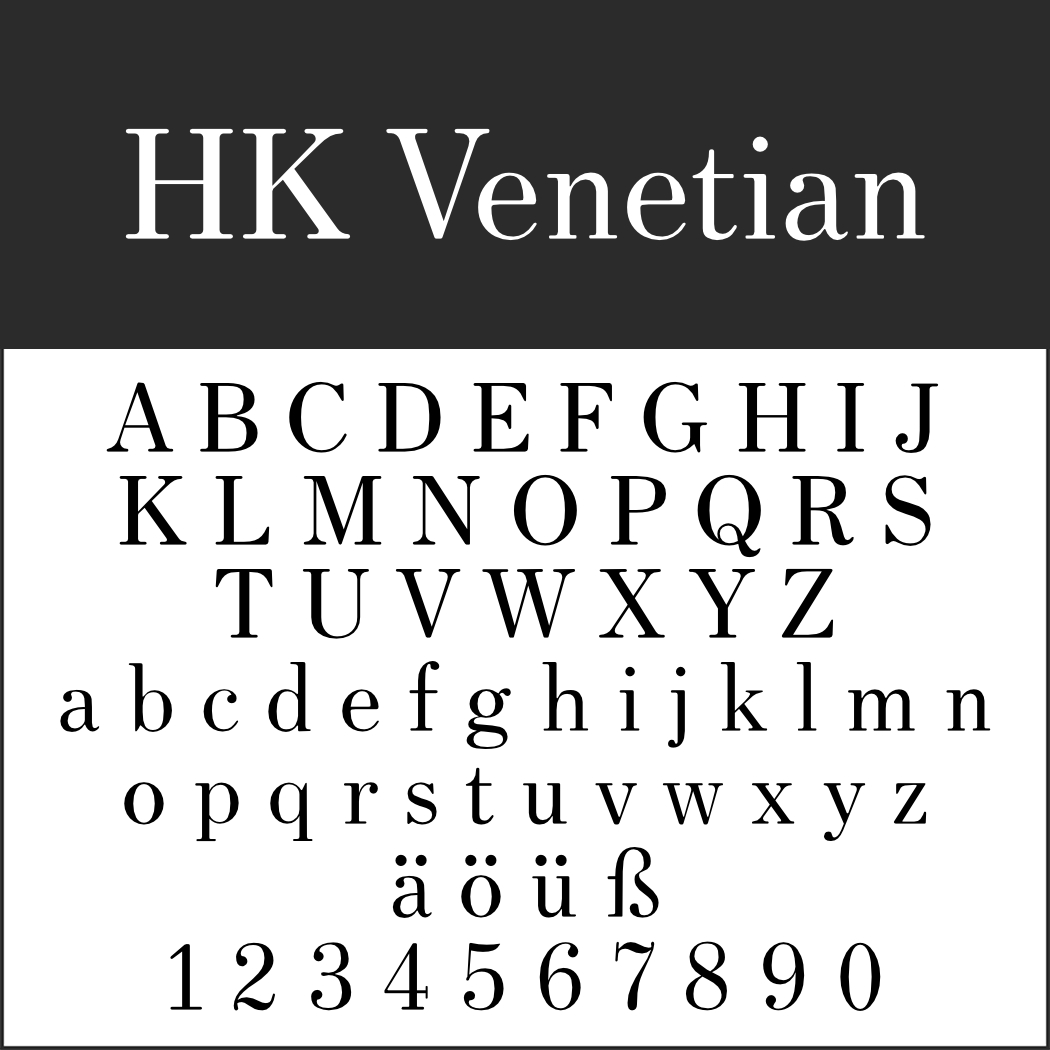
Schlichte Schriftarten lassen uns zunächst eher an Groteskschriften denken. Aber auch Serifenschriften können durchaus einfach wirken. In unserer Auswahl finden Sie beides.
Anek Telugu
Der indische Font aus Mumbai bietet acht Schriftstärken von Thin bis ExtraBold und ist deswegen sehr vielseitig einsetzbar.
Pianaforma
Pianaforma besticht durch runde, schlichte Formen mit ausgeprägter Mittellänge.
• Design: Meandro
Schlichte SchriftartenPistara
Pistara wirkt trotz seiner Einfachheit elegant und stellt quasi das Gegenstück zu Pianaforma dar. Denn hier fallen die Mittellängen auffallend niedrig aus.
Primer
Für diese schlichte Schriftart ließ sich der Designer von gedruckten Anleitungen aus dem Erziehungsbereich inspirieren.
Schlichte SchriftartenPontano Sans
Pontano Sans ist für Bildschirme optimiert, eignet sich aber genauso gut für gedruckte Texte.
• Design: Vernon Adams
Schlichte SchriftartenJunicode
Junicode verströmt mittelalterliches Flair und gibt sich für eine Serifenschrift betont schlicht.
• Design: Peter S. Baker
Schlichte SchriftartenSánchez
Die Slab-Serifschrift aus Chile wirkt ohne große Extravaganzen.
DejaVu
Passend zu dieser schlichten Serifenschrift gibt es eine Sans-Variante (DejaVu Sans) und eine Monospace-Version (DejaVu Sans Mono).
HK Venetian
Dieser Font soll die Schrift Venetian von Morris Fuller Benton wiederbeleben.
• Design: Hanken Design Co.
Schlichte SchriftartenLinguistics Pro
Schwungvoll, aber ohne Schnörkel: Linguistics Pro zählt zu den klaren Serifenschriften.
Taviraj
Ob Tairaj noch als schlichte Schriftart durchgeht, ist Interpretationssache.